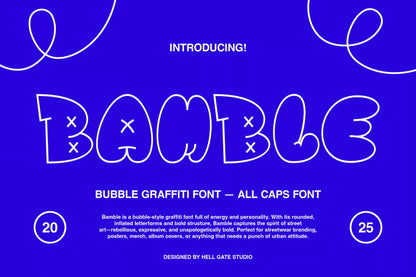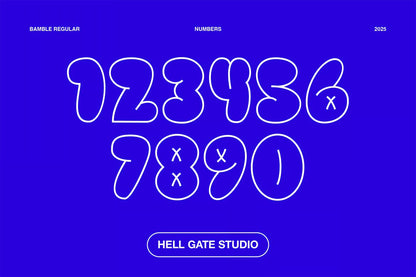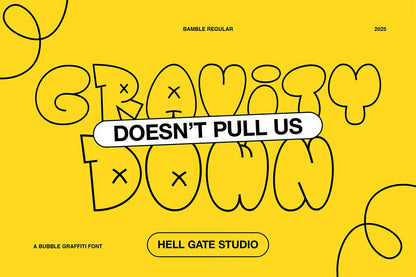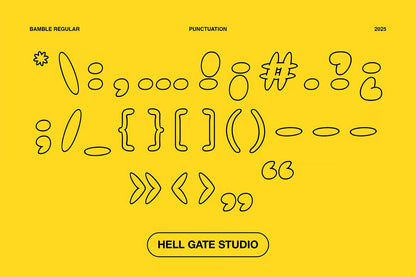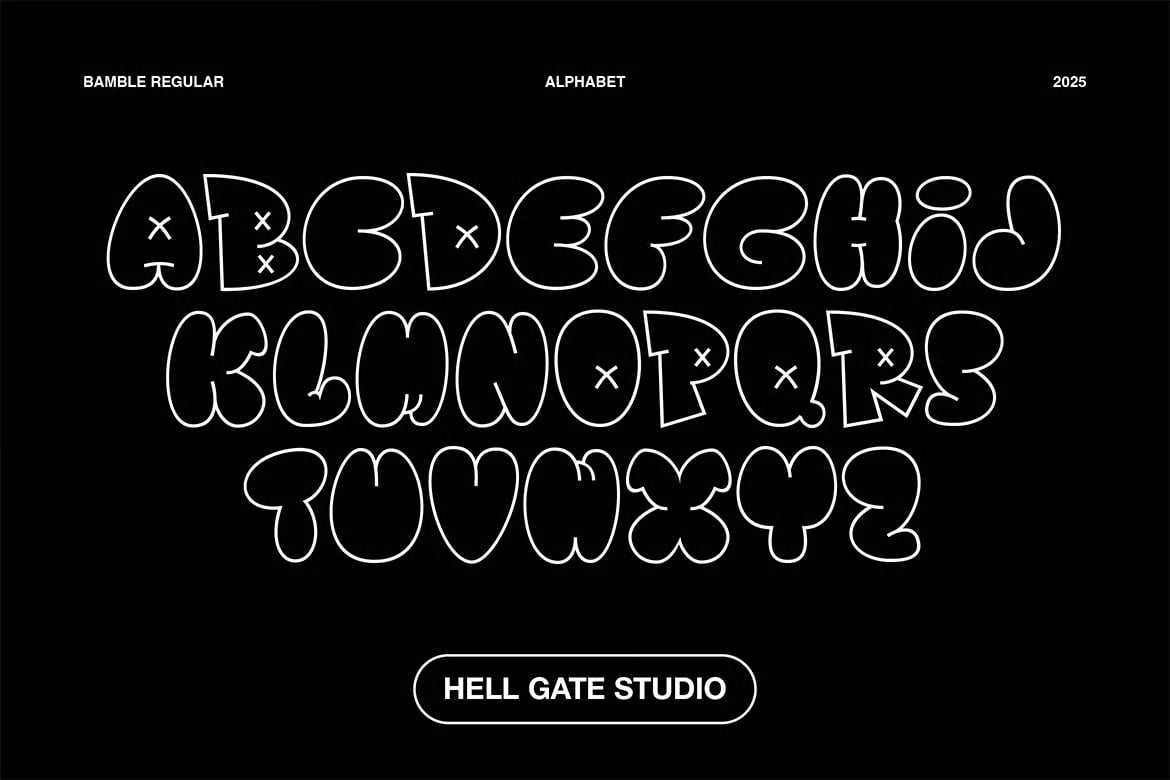
Bamble Graffiti Font
Découvrez Bamble, une police de caractères de style "bubble graffiti" débordante d'énergie et de personnalité. Avec ses lettres arrondies et gonflées et sa structure audacieuse, Bamble capture parfaitement l'esprit de l'art de rue, à la fois rebelle, expressif et sans complexe.
Conçue par HELL GATE STUDIO, Bamble est une police entièrement en majuscules, idéale pour :
-
Le branding de streetwear
-
Les affiches dynamiques
-
Le merchandising
-
Les pochettes d'album
-
Et tout ce qui a besoin d'une touche d'attitude urbaine et audacieuse.
Caractéristiques Clés :
-
Alphabet Complet (Majuscules) : Toutes les lettres de A à Z avec un design unique de bulles et de marques de "X" incrustées pour un look authentique.
-
Chiffres Expressifs : Une série complète de chiffres de 0 à 9, reprenant le style arrondi et ludique de la police.
-
Ponctuation Variée : Inclut un large éventail de signes de ponctuation et de symboles spéciaux pour compléter vos créations.
-
Style Urbain Authentique : Incarne l'esprit du graffiti avec des formes épaisses et un aspect manuscrit distinctif.
-
Polyvalente : Parfaite pour les designs qui nécessitent un impact visuel fort et une ambiance jeune et moderne.
Laissez Bamble donner vie à vos projets avec son esthétique audacieuse et sa personnalité contagieuse !